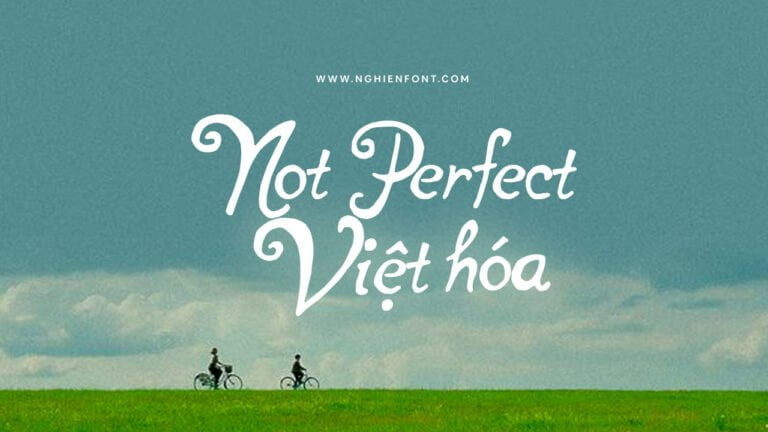
Font việt hóa Not Perfect là kiểu chữ viết tay ấn tượng với các nét chữ được thiết kế giống như chữ viết bút lông mang đến cảm giác mềm mại và đẹp mắt tô thêm vẻ đẹp cho tác phẩm của bạn.
Với có nét chữ có vẻ ngoài hơi dày, đậm một chút phù hợp để sử dụng cho nhiều thiết kế khác nhau như thiệp mời, trang trí, tạp chí, bìa truyện, quotes, typography hoặc bất kỳ thiết kế nào khác cần một kiểu chữ viết tay cổ điển.